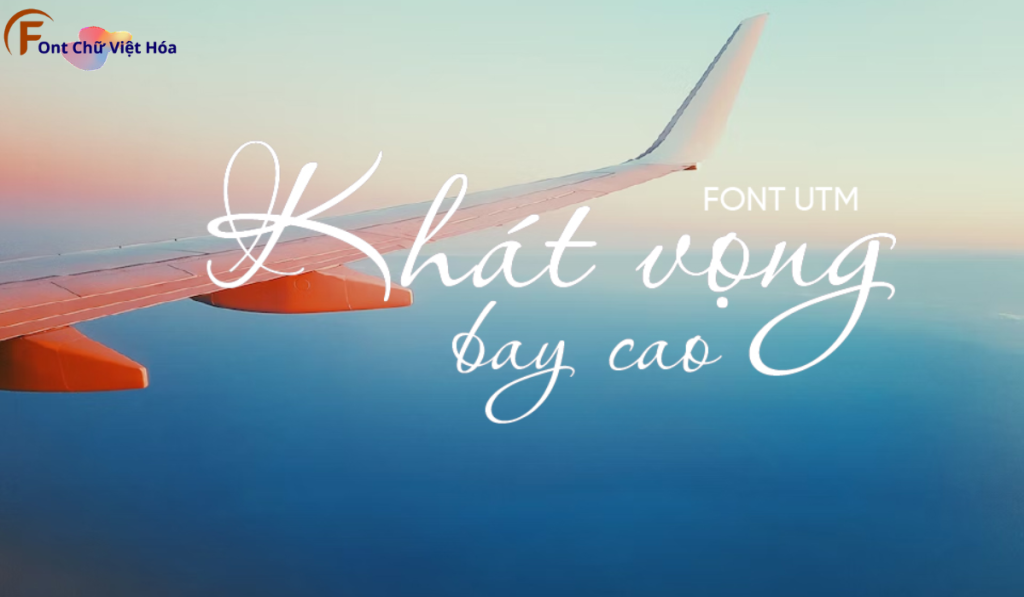
Font UTM Aquarelle Việt Hóa
Phân loại: Cá tính, độc đáo
Kiểu chữ: Chữ thảo
Font UTM Aquarelle Việt Hóa là một font chữ thảo mềm mại, thuộc bộ font UTM. Được thiết kế với mục tiêu mang lại sự tinh tế và nghệ thuật, font này lý tưởng cho các dự án thiết kế như thiệp mời, bìa sách, và các sản phẩm thủ công. Với các nét chữ uyển chuyển và độ dày đều đặn, Font UTM Aquarelle Việt Hóa không chỉ dễ đọc mà còn tạo cảm giác thanh lịch và sáng tạo. Việc Việt hóa font giúp người dùng dễ dàng tích hợp vào các thiết kế tiếng Việt, mang lại sự tiện lợi và nâng cao tính thẩm mỹ.